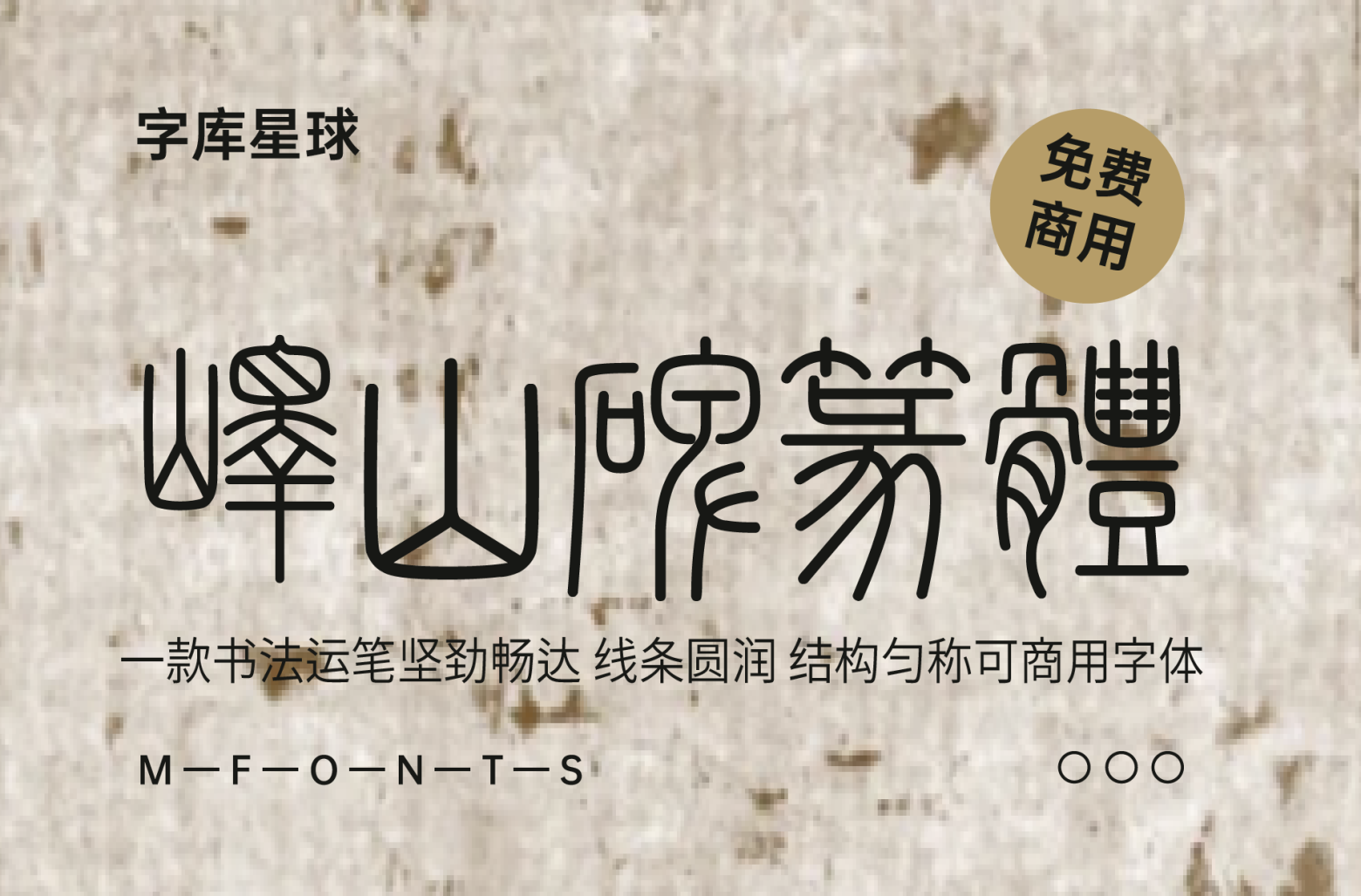
峄山碑篆体
这款篆书字体是咸阳职业技术学院在校学生大学生科技创新项目《峄山石刻字库开发》的成果,指导教师陈业欣,张家佳特战团与学校合作指导出品。
《峄山刻石》是秦统一文字后做的文章,传为李斯所书。李斯书法运笔坚劲畅达,线条圆润,结构匀称,点画粗细均匀,法度森严,安稳牢靠,和谐。突出地表现了统一、严整、理性精神与宏毅的内在力量。既具图案之美,又有飞动之势。
后人评价其书艺之高超掩灭先轨,散绝后贤,使一切写小篆的人皆难入其境,被称为篆书第一碑,成为后世临摹学书之佳作。
虽然困难重重,从去年8月起我们开始开发这款秦篆古风的复刻字库。本作品使用电脑路径对碑中文字进行临摹复刻。修补残破,使之焕然一新,充分展示出原碑原字应有的风采。
碑体以外文字的基本字型,我们选择了汉代许慎著,唐李阳冰勘定的《说文解字》。把总结的字型部首尽可能自然的应用到其他的篆书字体上。力求体现《峄山碑》原貌。